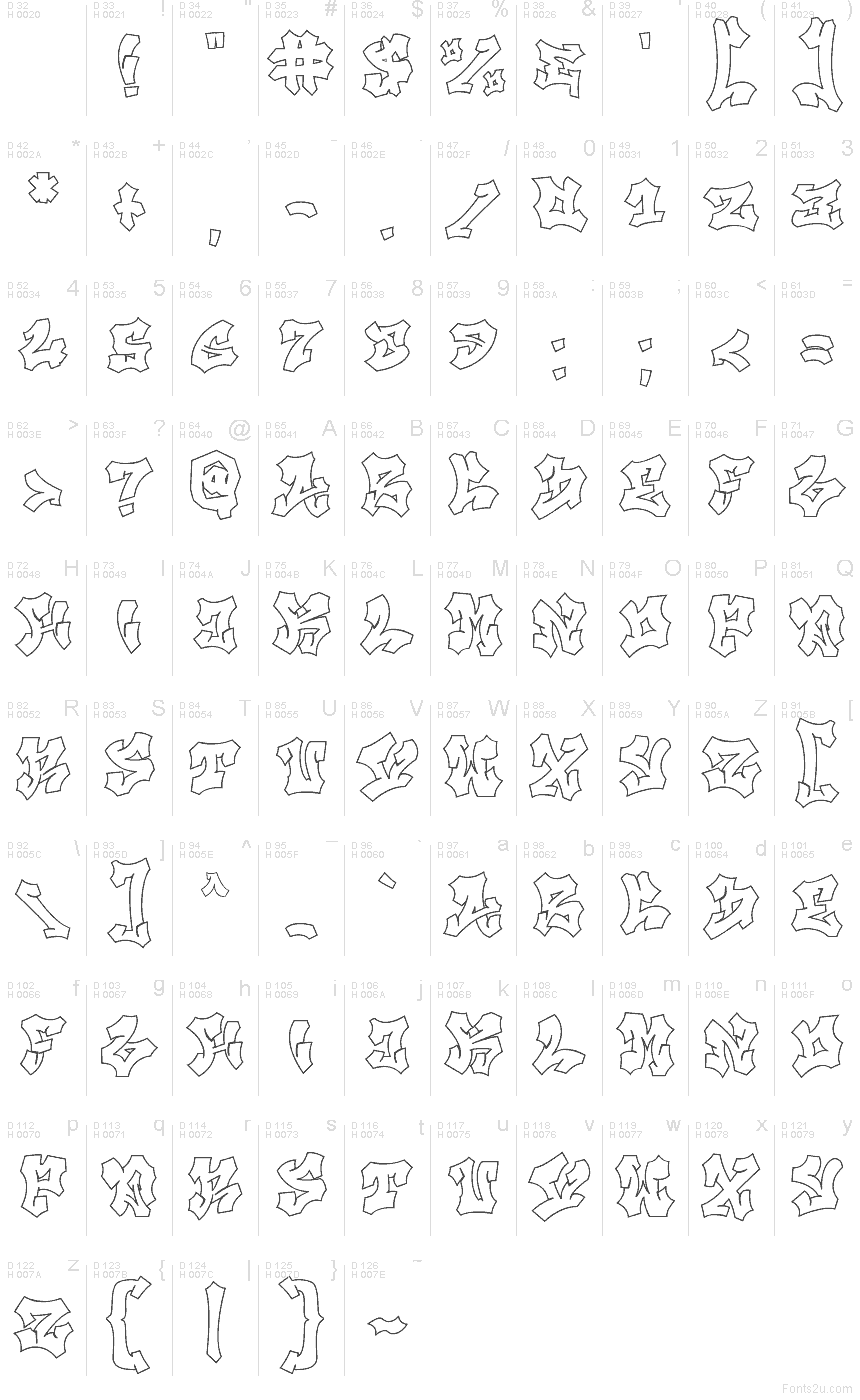
Beast Quotz Outline di Muhammad Panji Ramdhani e Ferbiya Rahmat di Sipanji x Cikareotype è un font graffiti gratuito. Il suo corrispondente, il carattere Beast Quotz, offre un look a contorno netto e irregolare che evoca il tratto manuale e l'anima street. Le lettere si incastrano con bordi frastagliati e un ritmo serrato, come segni di pennarello su carta strappata: un carattere di impatto, ma ben leggibile se gli si concede il giusto spazio.
Beast Quotz Outline brilla su poster hip-hop, loghi skate o streetwear, copertine di album, miniature gaming, pacchetti di sticker, volantini di eventi e titoli incisivi per YouTube o Twitch. Usalo in grande formato per far risaltare il contorno e abbinalo a un sans serif geometrico pulito per il testo di supporto, così da tenere sotto controllo il caos visivo. Questo font gratuito ha abbastanza grinta da sostenere un titolo senza bisogno di effetti aggiuntivi.